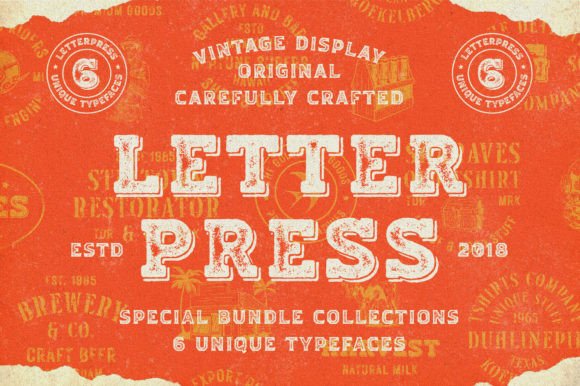
Letterpress
Mit Präzision gefertigt, bietet Letterpress saubere Vektoren, eine reibungslose Typografie und eine kommerzielle Lizenz für ein beruhigendes Gefühl.